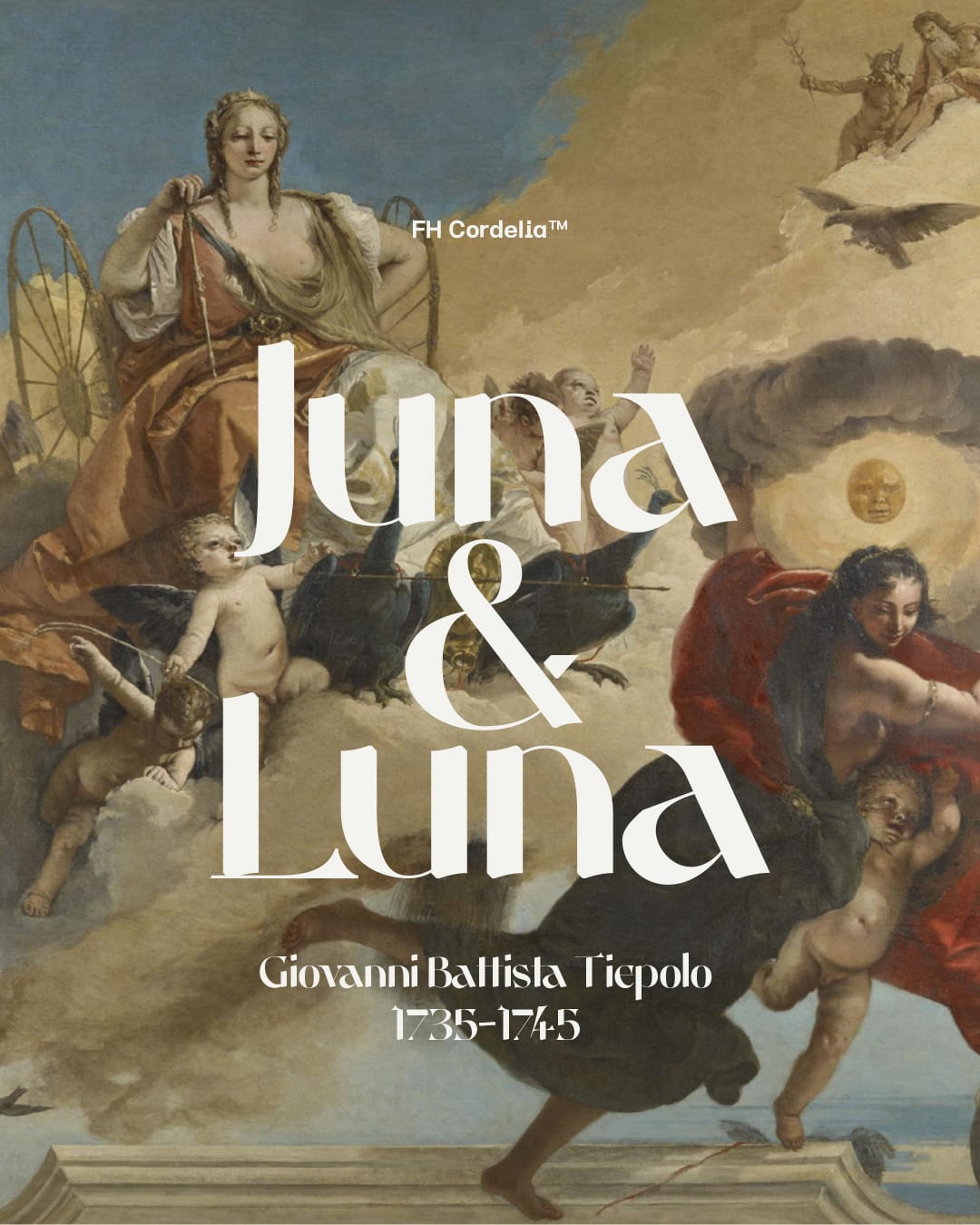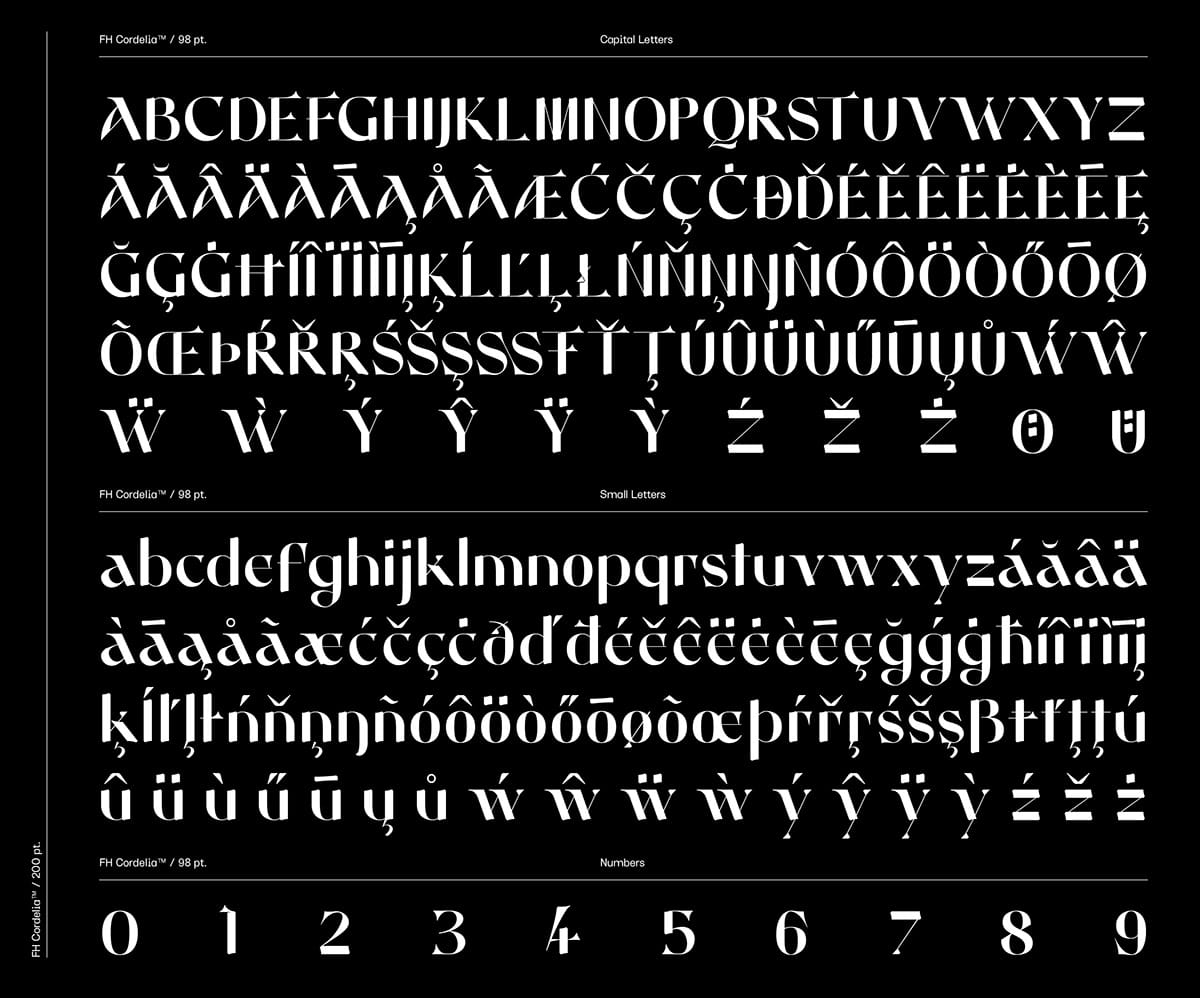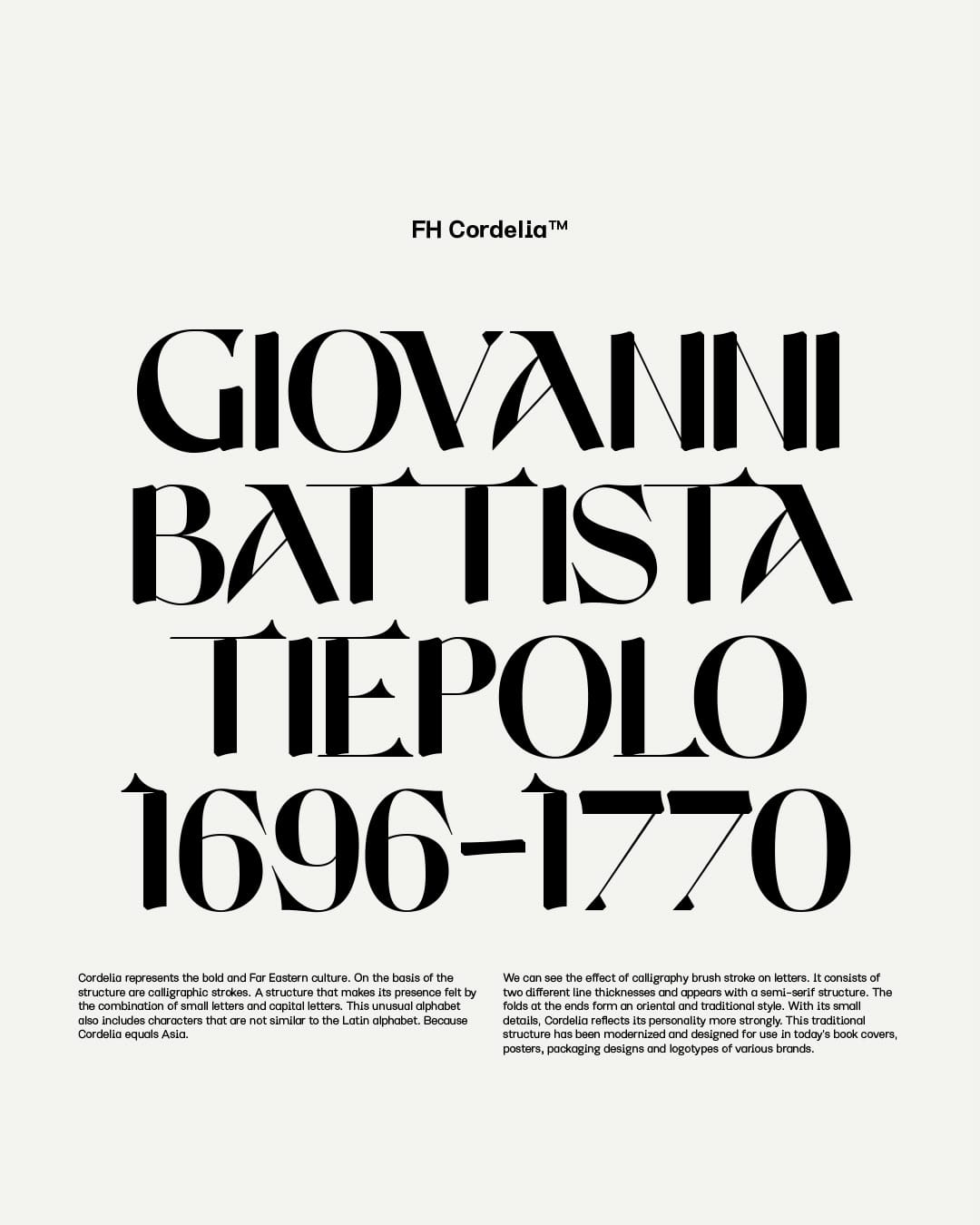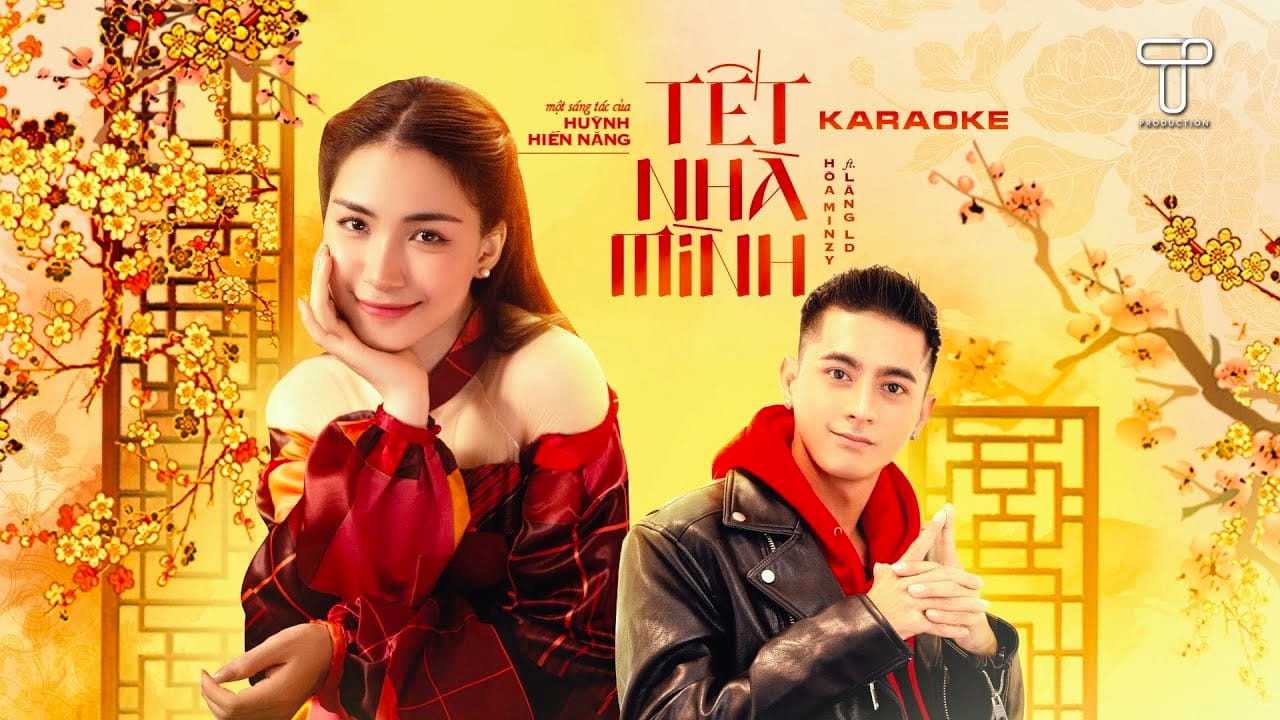
Hôm nay mình xin chia sẻ đến các bạn một font chữ rất đẹp sử dụng là
font bài hát Tết Nhà Mình | Hòa Minzy x Lăng LD
đó là font chữ
FH Cordelia . Font chữ này chưa Việt Hóa nhé các bạn, tuy nhiên các bạn có thể sử dụng Glyphs để ghép dấu.
Cordelia với các nét thư pháp. Một cấu trúc tạo nên sự hiện diện của nó nhờ sự kết hợp của các chữ cái nhỏ và chữ in hoa. Nó bao gồm hai độ dày khác nhau. Các nếp gấp ở đầu tạo thành một phong cách phương Đông và truyền thống. Với những chi tiết nhỏ, Cordelia phản ánh cá tính của nó mạnh mẽ hơn. Cấu trúc truyền thống này đã được hiện đại hóa và được thiết kế để sử dụng trong bìa sách, áp phích, thiết kế bao bì và biểu trưng của nhiều thương hiệu ngày nay.
Font FH Cordelia Display Việt Hóa